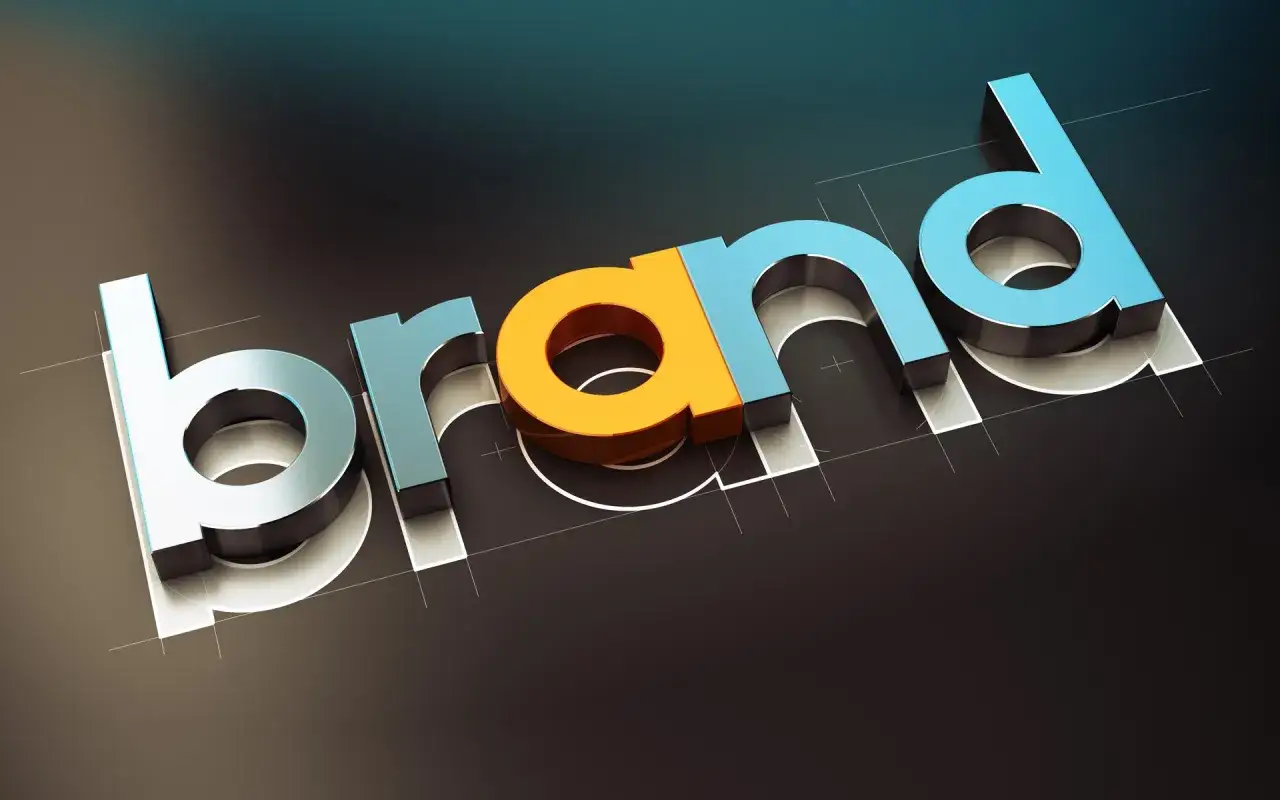
Typografia decyduje o tym, czy tekst prowadzi wzrok, buduje zaufanie i wspiera przekaz, czy tylko zajmuje miejsce na stronie. W tym artykule wyjaśniam, czym jest typografia, z jakich elementów się składa, jak wpływa na markę i czytelność oraz jak dobierać ustawienia, żeby projekt wyglądał profesjonalnie. To temat ważny nie tylko dla grafików, ale też dla marketingu, reklam i każdego miejsca, w którym liczy się szybki odbiór treści.
Typografia porządkuje treść, a nie tylko ją ozdabia
- To sztuka i technika układania pisma tak, by tekst był czytelny, spójny i skuteczny komunikacyjnie.
- O jej jakości decydują m.in. krój pisma, wielkość, interlinia, kerning, tracking i długość wiersza.
- Dobra typografia pomaga marce wyglądać pewniej, a treściom być łatwiejszymi do przeczytania.
- Na stronach internetowych zwykle lepiej działa prosty układ, wyraźna hierarchia i ograniczona liczba krojów.
- Najczęstsze błędy to zbyt mały tekst, zbyt długie linie, słaby kontrast i przypadkowe mieszanie fontów.
Czym właściwie jest typografia
Najkrócej mówiąc, typografia to sposób projektowania tekstu: dobór kroju, jego wielkości, odstępów, rytmu i układu, tak aby treść była wygodna w odbiorze. Gdy ktoś pyta, co to typografia, odpowiadam zwykle prosto: to język wizualny pisma, który decyduje nie tylko o estetyce, ale też o tym, jak szybko i jak dobrze czyta się komunikat.
Ważne jest też rozróżnienie pojęć, które często są mieszane. Krój pisma to projekt liter, font to jego cyfrowa postać lub konkretna odmiana, a typografia obejmuje sposób użycia tych znaków w całościowym projekcie. Innymi słowy: sam wybór fontu nie wystarcza, jeśli później tekst jest źle rozstawiony, zbyt zbity albo chaotycznie wyrównany.
W praktyce typografia pracuje zawsze tam, gdzie tekst ma coś zrobić: wyjaśnić, sprzedać, uporządkować, zbudować nastrój albo poprowadzić użytkownika po stronie. I właśnie dlatego nie jest dodatkiem do projektu, tylko jednym z jego głównych narzędzi.
Z czego składa się dobra typografia
Żeby dobrze ocenić tekst, trzeba patrzeć szerzej niż na sam font. Ja zwykle rozkładam typografię na kilka elementów, bo dopiero ich połączenie daje efekt, który naprawdę działa w praktyce.
| Element | Co kontroluje | Dlaczego ma znaczenie | Najczęstszy błąd |
|---|---|---|---|
| Krój pisma | Charakter liter i ton komunikacji | Buduje pierwsze wrażenie i dopasowuje tekst do marki | Wybór kroju tylko dlatego, że wygląda „ładnie” |
| Wielkość pisma | Jak łatwo tekst da się odczytać | Wpływa na komfort czytania i hierarchię informacji | Zbyt mały tekst główny, zwłaszcza na telefonie |
| Interlinia | Odstęp między liniami | Ułatwia skanowanie akapitów i zmniejsza zmęczenie wzroku | Zbyt ciasne linie, które „sklejają” akapit |
| Kerning | Odstęp między konkretną parą znaków | Poprawia wygląd nagłówków, logotypów i dużych napisów | Ignorowanie dziur między literami |
| Tracking | Ogólny rozstrzał liter w słowie lub bloku tekstu | Porządkuje rytm i może nadać tekstowi lekkości albo ciężaru | Przesadne rozciąganie lub ściskanie całych akapitów |
| Długość wiersza | Ile znaków mieści się w jednej linii | Wpływa na tempo czytania i koncentrację | Za szerokie kolumny, po których oko gubi początek następnej linii |
| Wyrównanie | Sposób ustawienia tekstu względem marginesu | Porządkuje blok tekstu i zmienia jego charakter | Justowanie bez kontroli łamania, które robi „rzeki” z białych przestrzeni |
| Kontrast i hierarchia | Różnice między nagłówkami, śródtytułami i tekstem podstawowym | Prowadzą wzrok i ułatwiają skanowanie treści | Wszystko wygląda podobnie, więc nic nie wybija się logicznie |
Przy tekście na stronie internetowej za dobrą bazę uważam zwykle około 16 px dla akapitu, interlinię w okolicach 1,4-1,6 i długość wiersza mniej więcej 45-75 znaków. To nie jest sztywny przepis, ale rozsądny punkt wyjścia, szczególnie gdy projekt ma działać na różnych ekranach. Kiedy te proporcje są złe, nawet ładny font przestaje pomagać.
Jeśli mam wskazać jedną rzecz, którą początkujący najczęściej bagatelizują, jest nią właśnie długość wiersza. Za szeroka kolumna męczy szybciej, niż wielu osobom się wydaje, dlatego w następnym kroku warto spojrzeć na typografię nie jako na detal, lecz jako na narzędzie wpływu na odbiór całej marki.
Jak typografia wpływa na markę i czytelność treści
Typografia robi dwie rzeczy naraz: upraszcza czytanie i ustawia ton komunikacji. Ten sam komunikat zapisany eleganckim, klasycznym krojem będzie kojarzył się z inną marką niż wersja oparta na prostym sans-serifie i mocnym kontrastowaniu nagłówków. W marketingu to ma realną wagę, bo odbiorca często ocenia wiarygodność projektu jeszcze zanim przeczyta pierwsze zdanie.
Na stronach internetowych typografia porządkuje ścieżkę użytkownika. Dobre nagłówki mówią, gdzie warto się zatrzymać, śródtytuły skracają czas skanowania, a odpowiednia interlinia pozwala czytać bez wysiłku. Złe ustawienia robią dokładnie odwrotnie: tekst wygląda na cięższy, niż jest w rzeczywistości, i użytkownik szybciej rezygnuje.